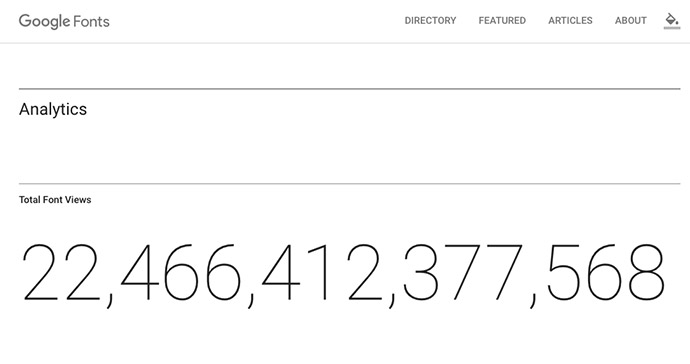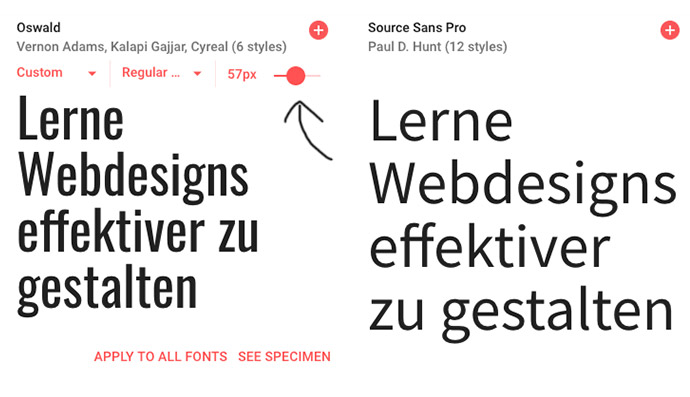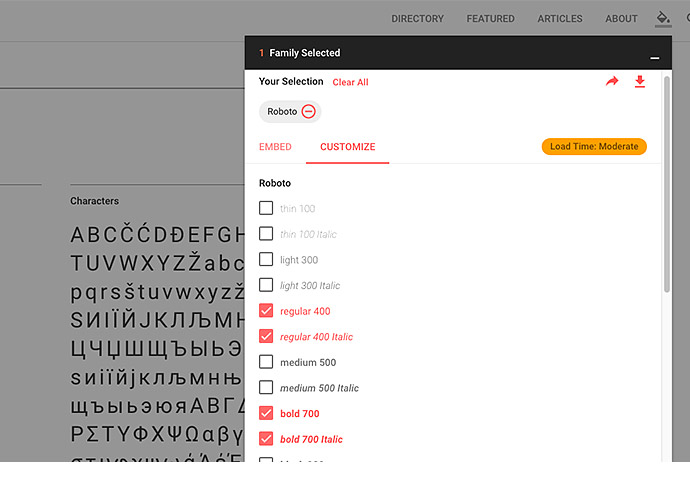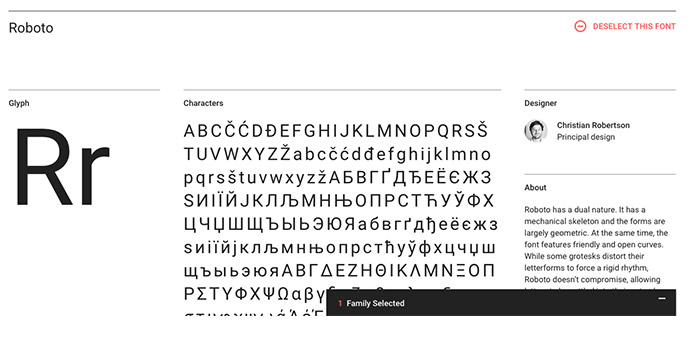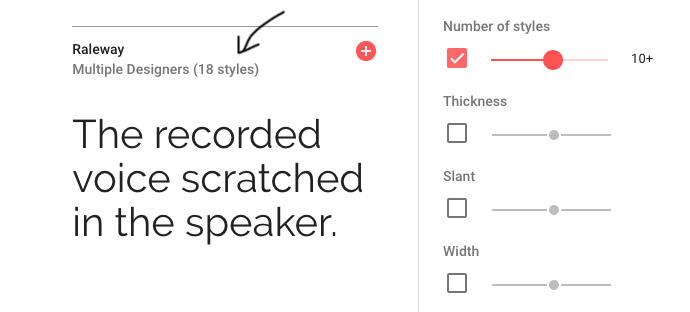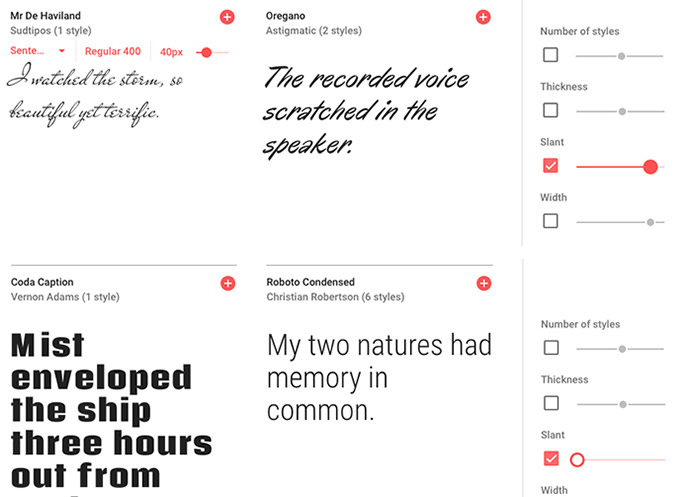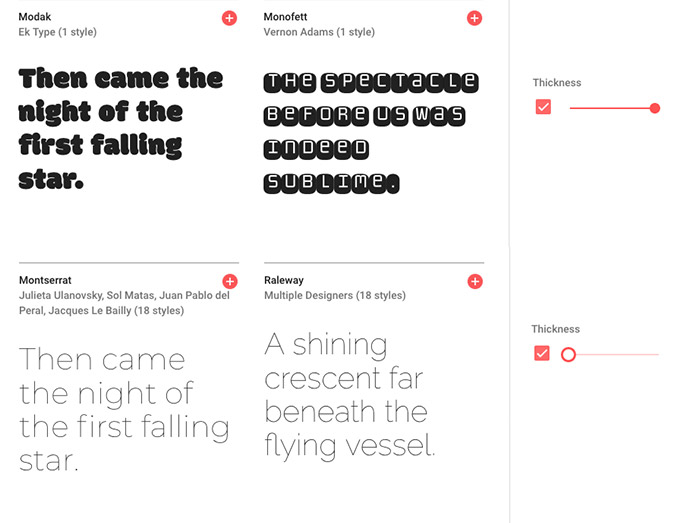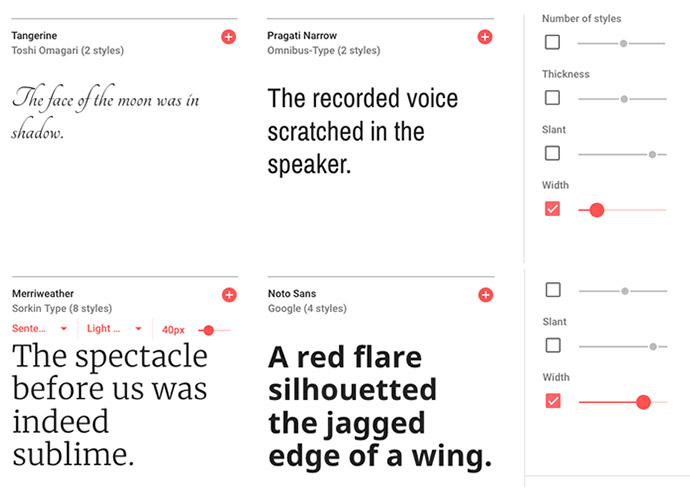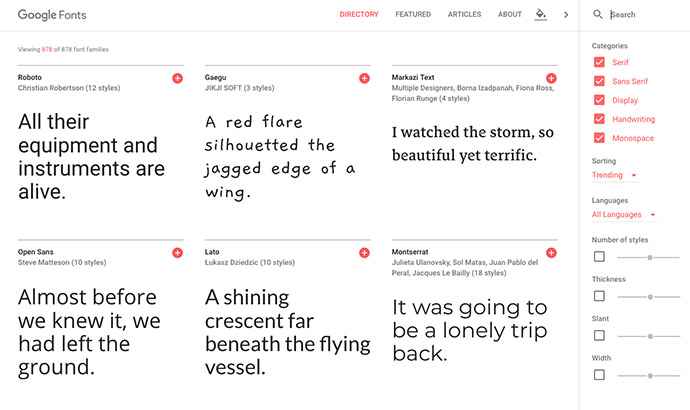
In den letzten Jahren haben sich Webfonts etabliert. Kaum mehr eine moderne Webseite, auf der sie nicht eingesetzt werden.
Erst durch Webfonts sind auch auf Webseiten ansprechende typografische Gestaltungen möglich, was vorher Printpublikationen vorbehalten war.
Die Web-Typografie hat inzwischen eine enorme Bedeutung. Was auch sinnvoll ist, da auch im Web die meisten Informationen textlicher Natur sind.
Möglich wurde dies aber erst durch die breite Auswahl an Schriftarten – den Webfonts eben – und die Unabhängigkeit von denen beim Nutzer installierten Schriften (den sogenannten Systemschriften).
Der beliebteste Webfonts-Dienstleister sind die Google Fonts.
Was genau sind die Google Fonts?
2010 gestartet sind die Google Fonts heute der beliebteste Webfonts-Anbieter.
Knapp 900 Schriftarten bietet der Suchmaschinenriese inzwischen an. Die Schriften kommen von verschiedenen Designern und sind sogenannte Open-Source-Fonts (d.h. mehr oder weniger frei benutzbar).
Google hostet die Schriften selber (also sie liegen sozusagen bei Google auf dem Server) und werden von dort geladen.
Sie sind kostenfrei kommerziell nutzbar. Also freier Einsatz auf jeder beliebigen Webseite. Das führt zu inzwischen zu über 22 Billionen (!) Seitenaufrufen, die Google Fonts einsetzen – eine unglaubliche Zahl.
Kein Wunder, ist der Dienst doch kostenlos, während bei anderen Anbietern meistens monatliche Gebühren bezahlt werden müssen.
Dazu kommt, dass die Schriften sehr einfach einzubinden sind. Mit einer einzigen Zeile Code steht eine eine riesige Auswahl an Schriften zur Verfügung.
Warum hat Google überhaupt eine Schriftensammlung?
Warum treibt sich eine Suchmaschine auf dem Fonts-Markt umher?
Im ersten Moment mag es etwas merkwürdig erscheinen, aber der Service hat für Google durchaus Sinn.
Google ist ein kommerzielles Unternehmen, das vom und für das Web lebt. Alles, was das Web besser und einfacher macht, ist auch für Google gut.
Und Webfonts machen das Web besser!
Eine bessere Suche
Bis vor wenigen Jahren hatten Webdesigner nur eine geringe Anzahl an weit verbreiteten Systemschriften zu Auswahl.
Oder Text als Bild abgespeichert.
Headlines, Buttons, Navigationspunkte – alles, was irgendwie typografisch etwas anders gestaltet sein sollte, musste in Photoshop erstellt und als Bild abgespeichert werden.
Die Verwendung von Bildern anstelle von HTML-Text ist aber schlecht. Zum Bearbeiten des Inhaltes muss ein Bildbearbeitungsporgamm geöffnet werden. Das Datenvolumen ist ungleich höher und damit die Ladezeiten der Seite. Und vor allem:
Google und Screenreader können die Texte in Bildern (noch) nicht indizieren. Die Suche ist aber Googles Kerngeschäft. Und je besser die Suchergebnisse sind, umso besser für Google.
Google Fonts hat maßgeblich dazu beigetragen, dass wir weniger „Text als Bild“ sehen, dafür mehr Webfonts.
Google will Daten
Natürlich will Google Daten, immer mehr Daten, unsere Daten.
Und natürlich wird Google gerne unterstellt, dass bei jedem Google-Dienst auch Daten gesammelt werden.
Ein offizielles Statement von Google sagt, dass durch die Google Fonts keine weiteren Daten gespeichert werden.
Ob man nun ein Problem mit einem eventuellen Datensammeln seitens Google hat, muss jeder für sich selber festlegen. Auf jeden Fall ist es mit der Datenschutzgrundverordnung (DSGVO) nicht mehr ganz so klar. Aber dazu später mehr…
Das Web ist Typografie
Der alte Spruch Web Design is 95% Typography zeigt im Grunde auch die Bedeutung von Webfonts für das Web und für Google.
Wenn Texte schneller und einfacher gelesen werden können, wenn Webseiten besser aussehen, wenn das Web also zu einem besseren Ort wird und immer mehr Menscher immer häufiger das Web nutzen, dann profitiert eben auch Google davon.
Gibt es auch Nachteile?
Google gibt den Webdesignern die Schriften nicht aus reiner Nächstenliebe. Es ist ein – vermutlich – kalkuliertes Geschäft.
Die Erfahrungen der letzten Jahre mit Angeboten wie dem Google Reader zeigen aber, dass dieses „Geschäft“ schnell uninteressant werden kann. Und dann kann recht schnell der Stecker gezogen werden.
Was wäre aber das Ergebnis, wenn Google den Font-Dienst einstellen würde?
Viele viele Webseiten, die mit Schriftarten wie Arial und Times glänzen. Nicht mehr und nicht weniger.
Doch auch bei kostenpflichtigen Webfonts-Anbietern ist man nicht davor gefeilt, dass die eines Tages pleite gehen.
Und sollte es wirklich einmal so weit kommen, könnte man die eingesetzten Google Fonts-Schriften, da Open-Source, herunterladen und selber hosten. Oder eben zu einem der anderen Anbieter wechseln.
Qualität der Schriften
Für „echte“ Typografen sind die angebotenen Schriften eher ein Ärgernis. Im Vergleich zu professionellen, kostenpflichtigen Fonts leidet die Qualität der Open-Source-Fonts oft an mindestens einer Stelle.
Mal bieten sie keine ausreichende Unterstützung von Sonderzeichen. Mal sind einzelne Buchstaben nicht fein ausgearbeitet und aufeinander abgestimmt (was Otto Normalverbraucher aber meistens nicht erkennt). Mal besitzen diese keine oder nur wenige Schriftschnitte.